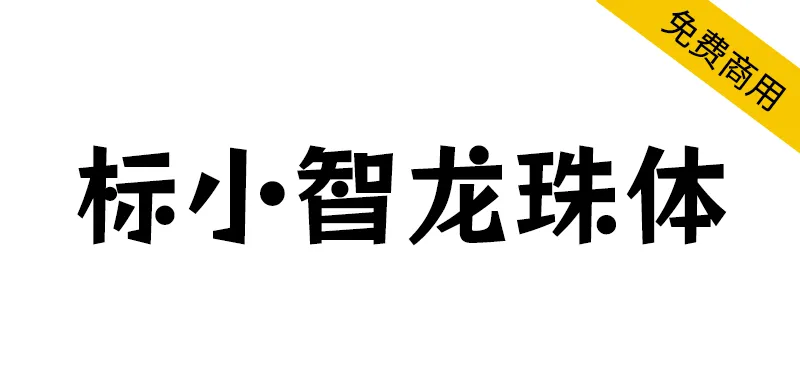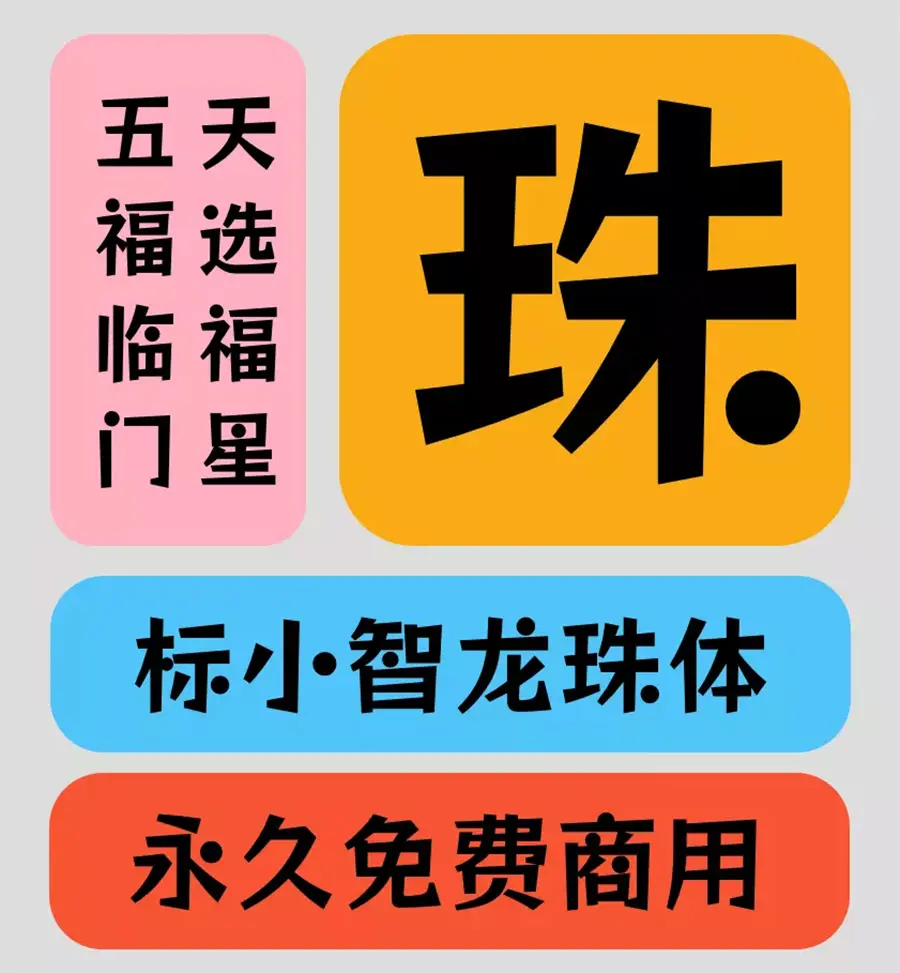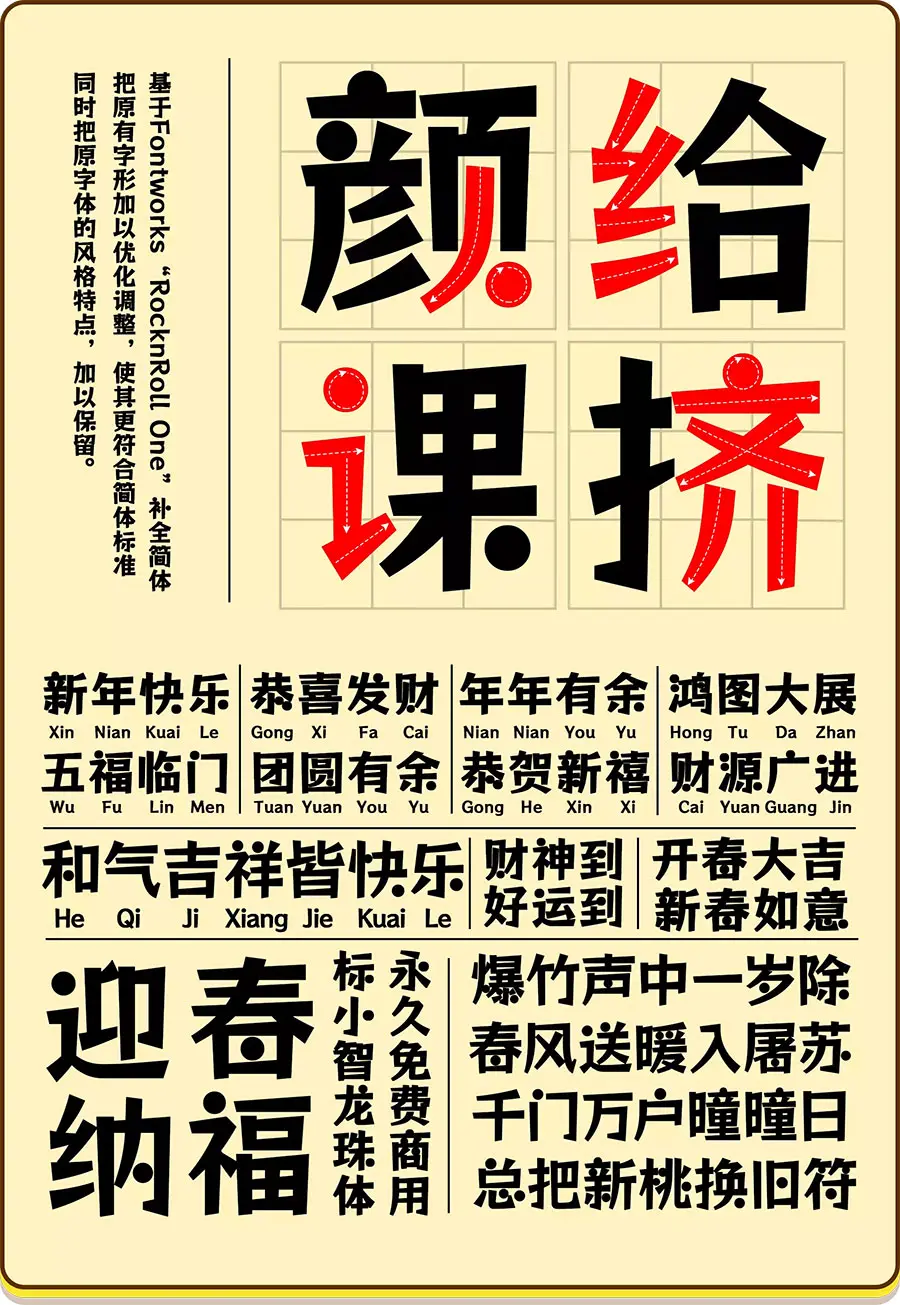
標小智龍珠體介紹
2022年我們發佈的首款免費商用字體標小智無界黑,受到了很多朋友的喜愛推薦。在2023年再次打造了一款卡通字體“標小智龍珠體”,允許任何個人和企業免費使用,包括商用用途,字體風格動感活潑俏皮可愛,非常適合用在卡通類logo設計中,來一起看看吧。
標小智龍珠體是基於日本著名字體設計公司Fontworks免費開源的搖滾樂 One(日文名:ロックンロール)字體進行簡體字補充的一款字體。
標小智龍珠體採用了原始的流行風格字體,力度不同的筆觸增加了動量,龍珠體整體上比較硬朗,字體筆畫粗細變化製作動感,而這款字體最大的特點就是這圓點(龍珠)點綴了,用龍珠代替部分筆畫,讓字體變得更加生動活潑,氣質也更加鮮明有記憶點,用來製作設計兒童卡通logo、標題文字、海報字效、橫幅標語等等,整體效果非常贊。